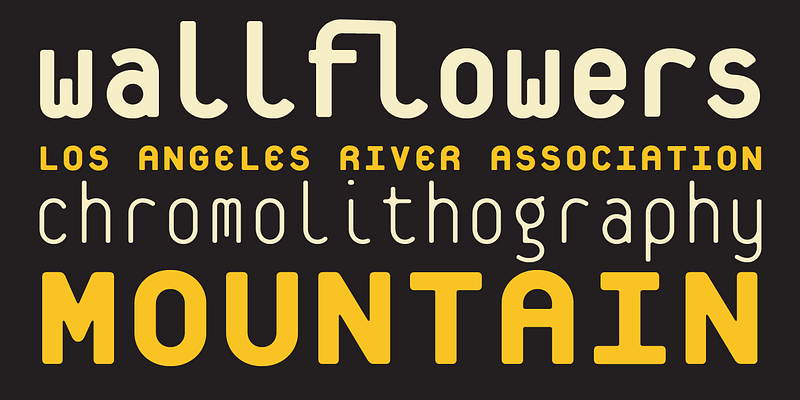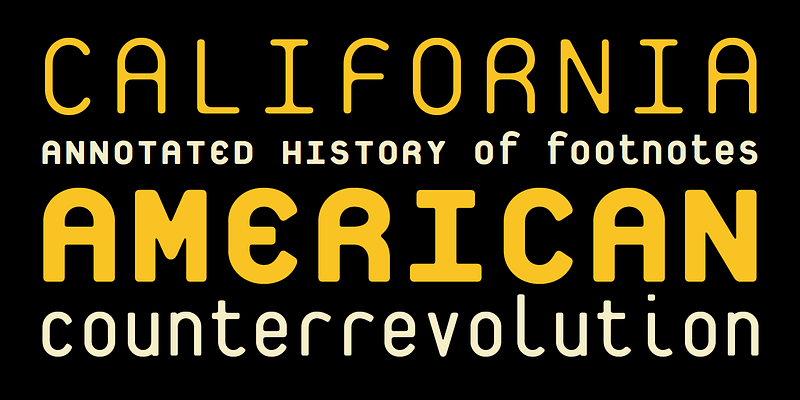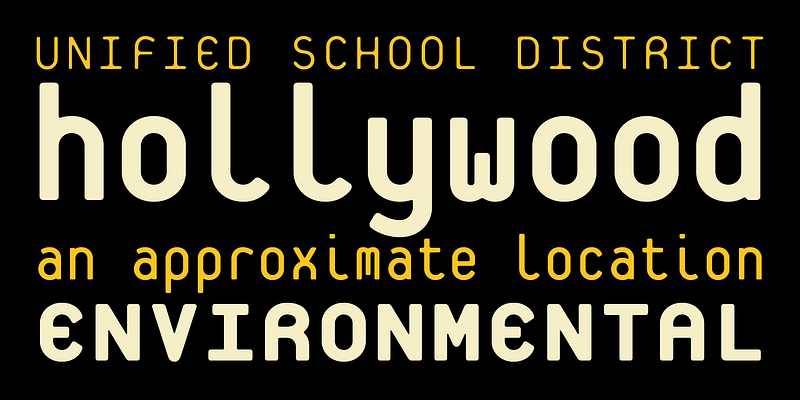
La inspiración para Platelet vino de la matrícula de California. Al igual que las restricciones de composición de la máquina de escribir, la fabricación de matrículas también requiere el uso de tipos monoespaciados; no solo por requisitos mecánicos, sino también para cumplir la necesidad de encajar un número fijo de caracteres en cada placa y maximizar su legibilidad a distancia.
Platelet contiene algunas soluciones inesperadas a los diversos problemas a los que se enfrentan los diseños monoespaciados. También ofrece soluciones que abordan la reducida legibilidad de los diseños geométricos, que tienden a hacer indistinguibles muchos caracteres, lo que reduce su función para las aplicaciones de texto. La “m” y la “w” resuelven inteligentemente el problema de la densidad de las tres plicas acortando la del medio. La “i” y la “l” no llenan su anchura con las serifas extendidas estándar, sino con un gran trazo curvo de salida. Otra solución creativa es la “b” minúscula, que incorpora la forma mayúscula dentro del carácter minúsculo. Esto aumenta el factor de reconocimiento de la “b”, que de otro modo sería muy similar a otros caracteres, como la “d”, debido a la rigidez geométrica de la construcción de la forma de letra de Platelet.